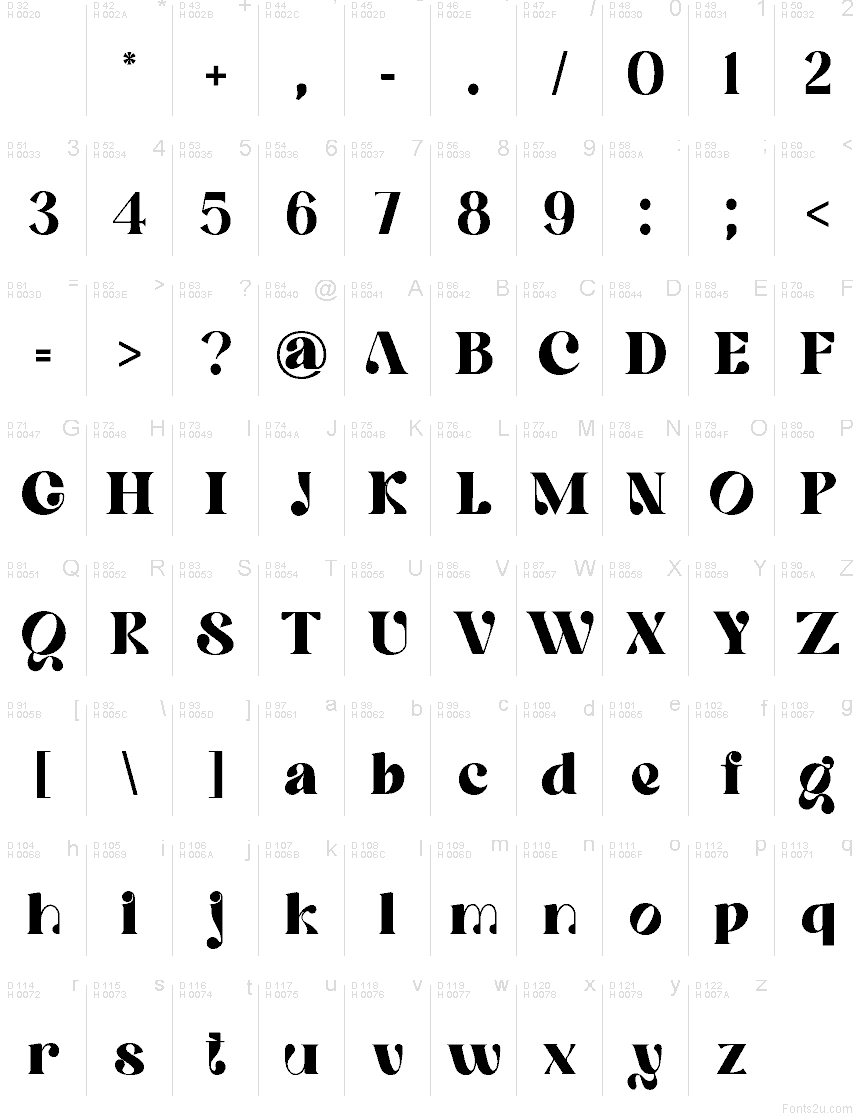
Quowist Display
Quowist Display d'Afkari Studio est une police avec empattements, gratuite et d'inspiration rétro, dotée d'une élégance résolument mode. Ses lettres misent sur un contraste marqué et des terminaisons arrondies en forme de goutte, conférant à cette police une esthétique éditoriale luxuriante, très années 70, tandis que ses courbes généreuses lui conservent un côté ludique plutôt que sévère.
Elle est idéale pour le branding, les packagings de boutiques, les couvertures de magazines, les titres d'affiches et les génériques, partout où vous recherchez une police gratuite au style marqué et féminin. Utilisez-la lorsqu'un mot ou une courte phrase a besoin d'être habillé en un instant, car ses courbes voluptueuses et ses détails travaillés font presque tout le travail pour vous.